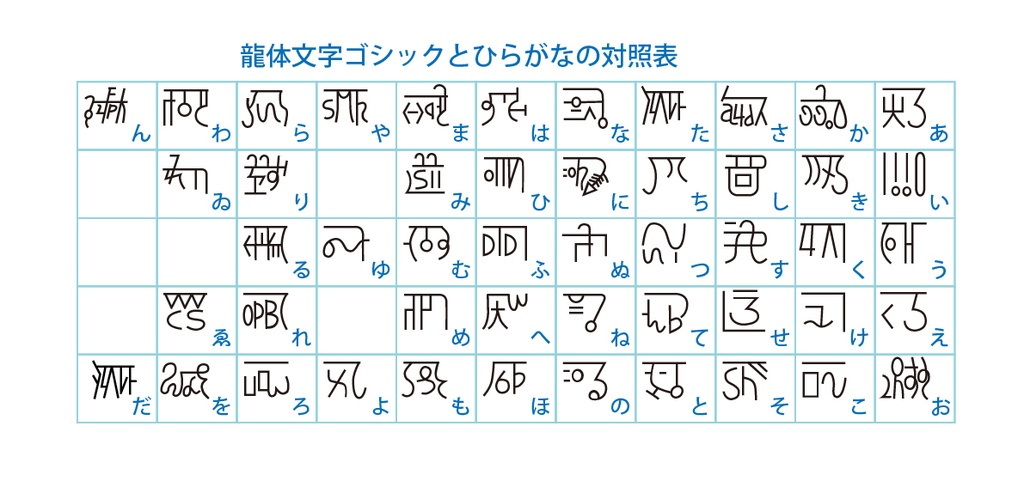
デジタルコンテンツ 龍体文字ゴシックフォント
龍体文字のゴシック体フォントです。 龍体文字Bと同様、なるべく正方形に近い字形にしています。 龍体文字とは神代文字の中でも最も古く5600年前に作られたと言われる文字。48字ある文字それぞれにパワーが宿っているとされています。 ひらがな48文字(ゐゑ含む)に対応した龍体文字があるので、ひらがなを入力すると相当する龍体文字が表示されるようにしました。 フォントファイルの形式はOpenTypeファイルです。 MacOS VenturaとWindows11での動作確認はしています。 【収録文字】 ひらがな(あいうえおかきくけこさしすせそたちつてとなにぬねのはひふへほまみむめもやゆよらりるれろわゐゑをん) ※濁音、半濁音、拗音、促音はありません。 ※「た」の龍体文字の書き方には2とおりあるようなので、異体字を「だ」に収録しました。 【データ内容・使用方法】 zipファイルを解凍してください。 OpenTypeファイル pkryutaig-Regular.otf JPGファイル(龍体文字とひらがなの対照表) comparison.jpg テキストファイル readme.txt が収録されています。 pkryutaig-Regular.otfをインストールしてください。 【購入の際の注意点】 商用利用OKです。 使用した場合、ご一報いただけるとうれしいです。Twitterなどで紹介します。 フォントファイルの改変・再配布は禁止です。